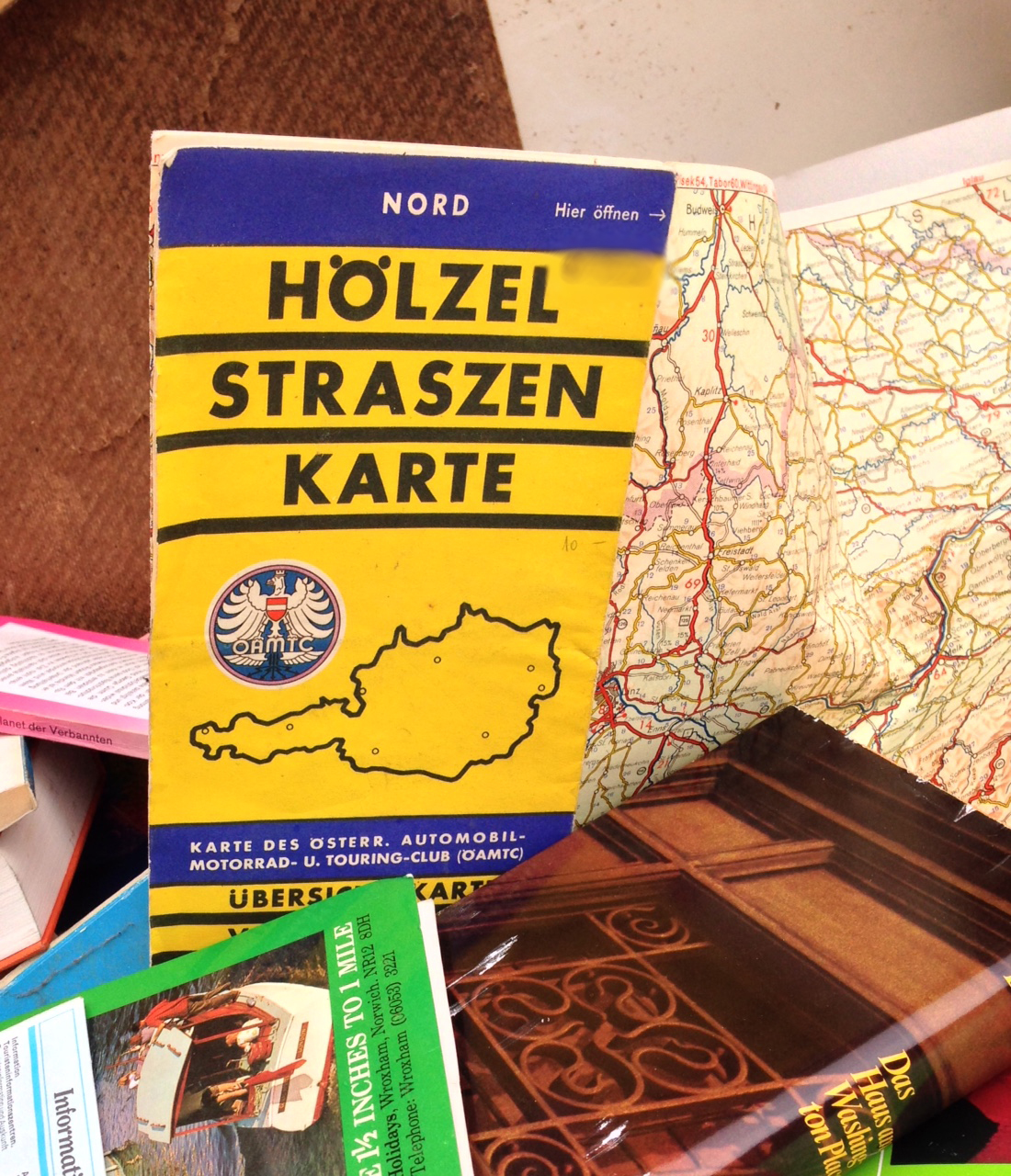
Da wurde wahrscheinlich eine Polymer-Auswaschplatte (da grün wird es ev. Torelief sein) mit Comic Sans-Typen erstellt, zugeschnitten und auf die Typenhebel geklebt. Mit der Methode könnte man sicher auch eine Fraktur-Schreibmaschine basteln.
War beim Sugar Moon Maple Syrup auch ein Produktdesigner beteiligt? Mir sieht das so aus, als gäbe das bei jedem Ausgießen eine Riesensauerei an der Flasche …
Das ist doch egal – Hauptsache es sieht hübsch aus ;-) könnte mir aber vorstellen, dass es problemlos geht, wenn man schnell genug gießt und nicht nur kleine Mengen entnimmt, was ja auch im Sinne des Hersteller ist :party:
Form follows … äh …  :hammer:
Na wer sollen denn sonst die Regeln infrage stellen, wenn nicht wir Jungen  :rockon:  :cheer:
War beim Sugar Moon Maple Syrup auch ein Produktdesigner beteiligt? Mir sieht das so aus, als gäbe das bei jedem Ausgießen eine Riesensauerei an der Flasche …
Schwer zu sagen. Der Hausmarken-Ahornsirup meiner Lieblingskaufhalle kommt auch in einer Glasflasche ohne Ausgießhilfe daher. Probleme mit dem Ausgießen kleiner Mengen hatte ich überraschenderweise nie. Vielleicht liegt das auch daran, dass reiner Ahornsirup auch bei Zimmertemperatur dünnflüssig ist. Olivenöl, das ab und an in vergleichbaren Flaschen verkauft wird, ist da deutlich problematischer.
Der letzte Ahornsirup, den ich bekommen habe, befand sich in Büchsen (original aus Kanada geschickt). Da muss man dann selber überlegen, in was für ein wiederverschließbares Gefäß man ihn füllen möchte.
Praktisch finde ich übrigens, wie man in Spanien Rohrzucker verpackt: Der wird in Tetrapacks mit Schraubverschluss verkauft. Das schützt den Zucker vor Feuchtigkeit, ist praktisch, weil man den Zucker gut lockerschütteln kann und eignet sich außerdem prima zum Dosieren.
Schau mal auf die Nummer 9 aus Tobis Link … Rohrohrohrzucker …
Roh-Rohr-Ohr-Zucker? Oder Rohr-oh-Rohr-Zucker? Oder Roh-Rohr-Ohr-Zucker? Oder Rohr-Ohr-Ohr-Zucker? Oder Roh-Roh-Rohr-Zucker? Und überhaupt: Zucker mit Ohren??  :shock:
Der letzte Ahornsirup, den ich bekommen habe, befand sich in Büchsen (original aus Kanada geschickt). Da muss man dann selber überlegen, in was für ein wiederverschließbares Gefäß man ihn füllen möchte.
Ich wollte eigentlich vorhin schon schreiben, dass echte Ahornsirupfans (»Sirupfan« hat auch tolles Kniffligkeitspotential, oder?) i.a.R. ohnehin einen wiederverwendbaren Sirupgießer verwenden. Die Dosiermöglichkeiten der Verkaufsverpackung sind also eher für Gelegenheitskäufer relevant. Vielleicht könnte ein Hersteller, der angibt, besonders bei Sirupexperten beliebt zu sein, sogar versuchen, das durch die Wahl einer eher schlecht am Tisch verwendbaren Verpackung zu kommunizieren? :-? Ahornsirup ist in manchen Regionen der USA ja ein echter Kult. Exklusivität kann im hart umkämpften Markt sicher nicht schaden.
(»Sirupfan« hat auch tolles Kiffligkeitspotential, oder?)
Ganz bestimmt – es fühlt sich danach ja manchmal schon so an als hätte man eine Wolldecke im Mund. Der Sirup kann da natürlich Abhilfe schaffen ...  :hammer:
Wieder mal ein herrlich passender ›Freudscher Vertipper‹.
buchstäbliche komik zur unterhaltung während der elternhausräumung …
Wieso Komik? Ich hätte das, wenn kein Versal-ß zur Verfügung stünde, nicht anders gemacht und halte das gegenüber der SS-Schreibung für die deutlich bessere Lösung.
weil ich, als mein 16-jähriger sohn mich aus der mulde heraus fragte, warum die österreicher ihre karten so irgendwie «tschechisch» beschriften, lachen musste. vielleicht?
warum die österreicher ihre karten so irgendwie «tschechisch» beschriften …
Nun ja, Böhmen war ja Bestandteil des Habsburgischen Reiches, von daher wäre das auch wieder nicht so abwegig.
Ich kenne die SZ-Schreibweise vorwiegend von Architekturplänen.
Da steht gerne MASZSTAB und ich finde es immer wieder schön :-)
Schweizer Kinder werden das natürlich noch verwirrender finden wie deutsche
Kinder,die das ß ja wenigstens aus dem normalen Gebrauch kennen.
Ich stolpere dagegenen immer bei Schweizer Lektüre über die schweizer
Rechtschreibung,
wie heute erst wieder im neuen Publisher.